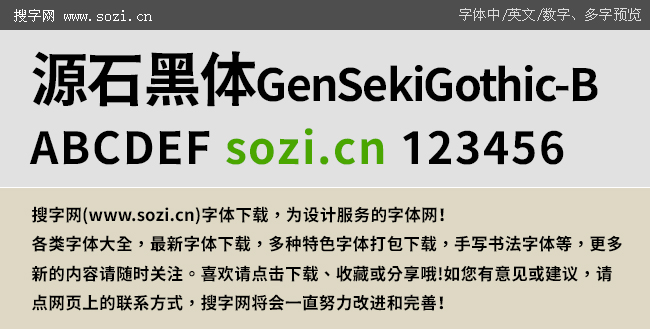
源石黑体GenSekiGothic-B
搜字网给大家提供一款源石黑体GenSekiGothic-Bt中文字体下载,源石黑体是基于思源黑体改造的一款字型。本字体则尝试重现早期年代较复古的黑体风格,较有温暖的气息。字体保留思源黑体所支持的所有汉字(包或日、韩文汉字与简体字),基本不会有缺字问题。 但由于这款字体是由程序自动生成,个别字可能会存在笔划错误,大家在使用时需要检查一下。适用于标题设计、海报设计、书籍排版以及网页设计等应用。